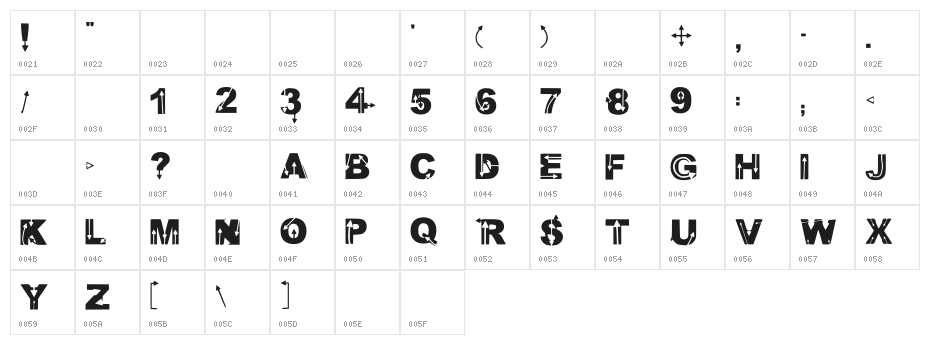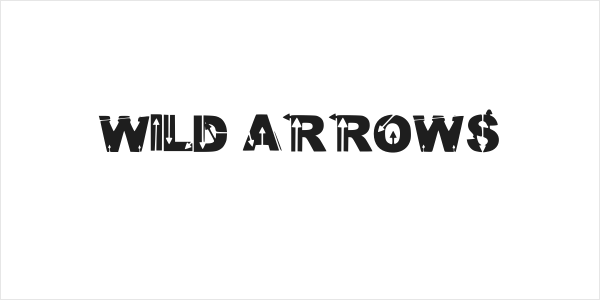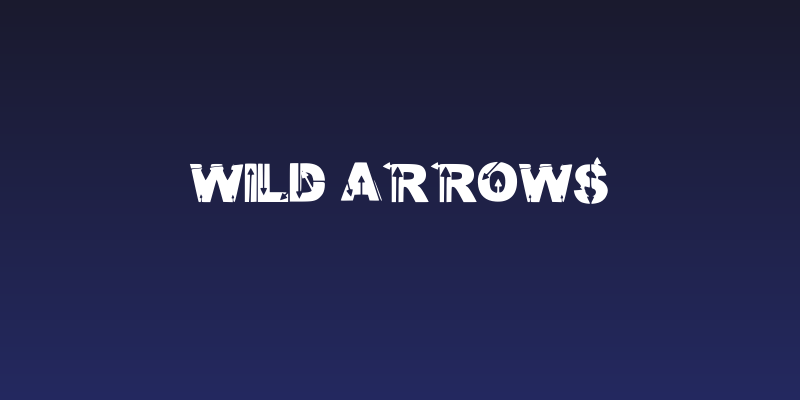
Wild Arrows Font
| Estilo general | Modern, Decorative |
| Proyectos propuestos | Ideal for adventure-themed posters, branding for outdoor activities, or any design needing a bold, directional aesthetic. |